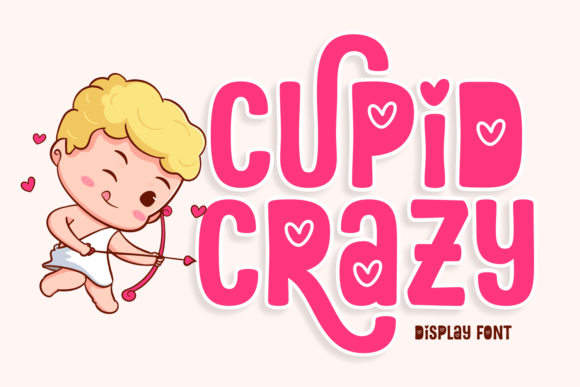
Cupid Crazy
Se você está procurando ativos de alta qualidade como Cupid Crazy, este pacote premium é uma escolha fantástica para seus projetos criativos.
Quer você esteja criando produtos POD (Print on Demand), convites de casamento ou gráficos para mídias sociais, Cupid Crazy é a escolha ideal.